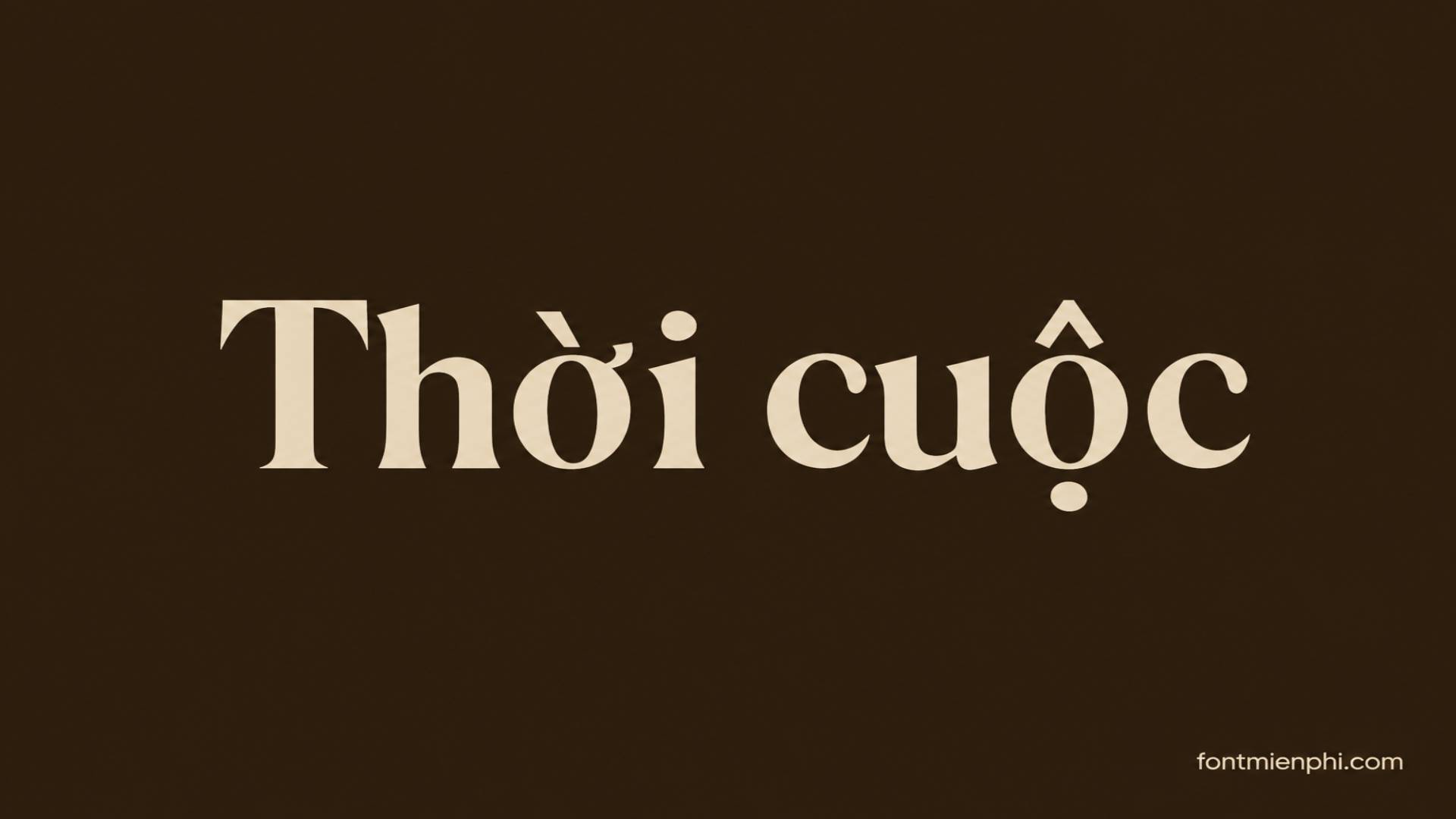
Bạn đang theo đuổi phong cách thiết kế hoài cổ (Retro/Vintage) hoặc muốn tìm một phông chữ mang đậm dấu ấn thời gian nhưng vẫn toát lên vẻ cao cấp? Font Việt hóa 1FTV VIP Roast Ledger chính là sự lựa chọn tuyệt vời nhất để biến các ý tưởng của bạn thành những tác phẩm nghệ thuật thực thụ. Nằm trong bộ sưu tập VIP đình đám của 1FTV, Roast Ledger mang trong mình nét đẹp cổ điển, ấm áp và vô cùng độc đáo.
1. Tổng quan về Font 1FTV VIP Roast Ledger
1FTV VIP Roast Ledger là một phông chữ được lấy cảm hứng từ những bản in ấn cổ điển, những cuốn sổ cái (ledger) từ thế kỷ trước và những bảng hiệu nhuốm màu thời gian. Cấu trúc của phông chữ mang dáng dấp của dòng Serif hoặc Slab Serif truyền thống, với các chân chữ vững chãi, đường nét dày dặn và đôi khi được nhấn nhá thêm một chút hiệu ứng “mực in xước” nhẹ nhàng, tạo ra một tổng thể vô cùng mộc mạc nhưng đầy khí chất.
Chữ “Roast” trong tên gọi cũng gợi lên cảm giác ấm áp, đậm đà giống như những hạt cà phê rang xay thủ công. Nhận thấy vẻ đẹp vượt thời gian của font chữ này, đội ngũ 1FTV đã chăm chút và Việt hóa tỉ mỉ từng chi tiết. Toàn bộ các dấu câu tiếng Việt được thiết kế lại để hòa quyện hoàn hảo với phong cách cổ điển gốc, không làm mất đi cái hồn hay gây ra cảm giác “lạc quẻ” thường thấy ở các bản font lỗi.
2. Đặc điểm nổi bật của Font Roast Ledger Việt Hóa
Thuộc phân khúc font VIP cao cấp, 1FTV VIP Roast Ledger sở hữu những ưu điểm vượt trội làm say lòng bất kỳ nhà thiết kế nào:
• Phong cách Vintage/Retro chân thực: Mang lại cảm giác hoài niệm, bụi bặm nhưng lại rất có gu, giúp ấn phẩm của bạn trở nên có chiều sâu và kể được câu chuyện riêng.
• Độ dày dặn và vững chãi: Trọng lượng chữ lớn giúp Roast Ledger thể hiện sức mạnh tuyệt đối khi làm tiêu đề chính, thu hút ánh nhìn ngay lập tức.
• Kerning Tiếng Việt chuẩn xác: Khoảng cách giữa các ký tự có dấu (như ơ, ư, ă, â) được xử lý thủ công, đảm bảo sự liền mạch và nhịp điệu hoàn hảo cho từng từ ngữ.
• Bộ ký tự nghệ thuật phong phú (Alternates): Cung cấp các ký tự thay thế để bạn thỏa sức biến tấu, tạo ra những logo hoặc tiêu đề trông giống như được vẽ tay (hand-lettering).
3. Ứng dụng thực tế của 1FTV VIP Roast Ledger trong thiết kế
Với tinh thần cổ điển và ấm áp, Font 1FTV VIP Roast Ledger là “vũ khí bí mật” cho các dự án đòi hỏi sự mộc mạc và cá tính:
Mẹo phối Font (Typography Tip): Để tạo nên một thiết kế Retro chuẩn mực, hãy dùng Roast Ledger làm tiêu đề chính (Heading). Sau đó, kết hợp nó với một font Sans-serif cơ bản, mỏng nhẹ hoặc một font Script (chữ viết tay) bay bổng cho phần nội dung phụ (Sub-text) nhằm tạo sự tương phản cực mạnh cho thị giác.
• Nhận diện thương hiệu (Branding): Sự lựa chọn số 1 cho logo của các quán Cà phê đặc sản (Specialty Coffee), tiệm bánh thủ công (Bakery), cửa hàng đồ da (Leather craft), hoặc các Barbershop mang phong cách cổ điển.
• Bao bì sản phẩm (Packaging): Nâng tầm bao bì cho các sản phẩm như cà phê rang xay, bia thủ công (Craft beer), xì gà, hoặc mỹ phẩm chiết xuất thiên nhiên.
• Thiết kế Poster & Áo thun (Typography): Cực kỳ phù hợp với các thiết kế áo thun Local Brand mang hơi hướng Streetwear cổ điển, hoặc poster các đêm nhạc Acoustic, sự kiện Vintage.
• Biển hiệu (Signage): Tạo ra những bảng hiệu giả cổ đầy ấn tượng cho các cửa hàng, nhà hàng trên phố.